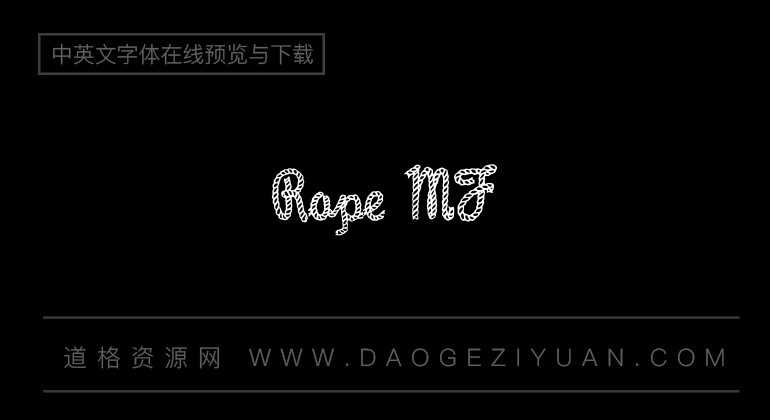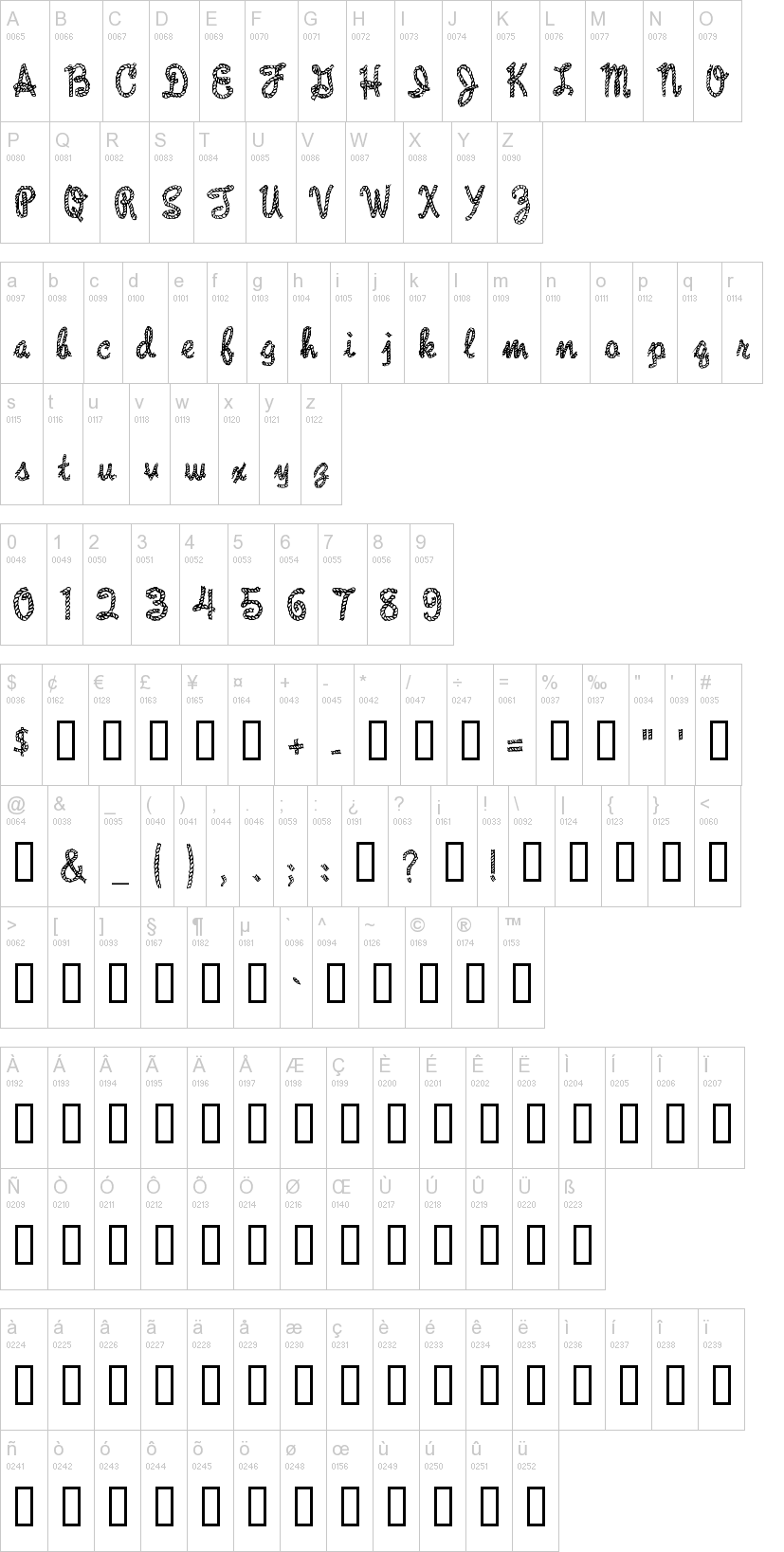
Rope MF
Rope MF 是一种经典的脚本字体,由英国设计师Paul Lloyd创作,它的特点是具有流畅的书写样式,拥有温柔的曲线,拥有柔和的氛围。它有着优雅的形状,细节处理得很好,用它来制作文字效果,会让文字更加柔和,给人一种温暖的感觉。Rope MF 字体适用于手写文字,书法,标题,海报,卡片等等,可以让文字充满活力,更加有趣。
Rope MF是一款非常不错的手写艺术字体,具有很好的视觉感,适合于文化类的宣传设计、商业类品牌的广告和产品包装设计以及个性化文字排版等较多场景。
Rope MF字符映射图